今回は、「炭」の書き方を解説します。
「炭」の見本
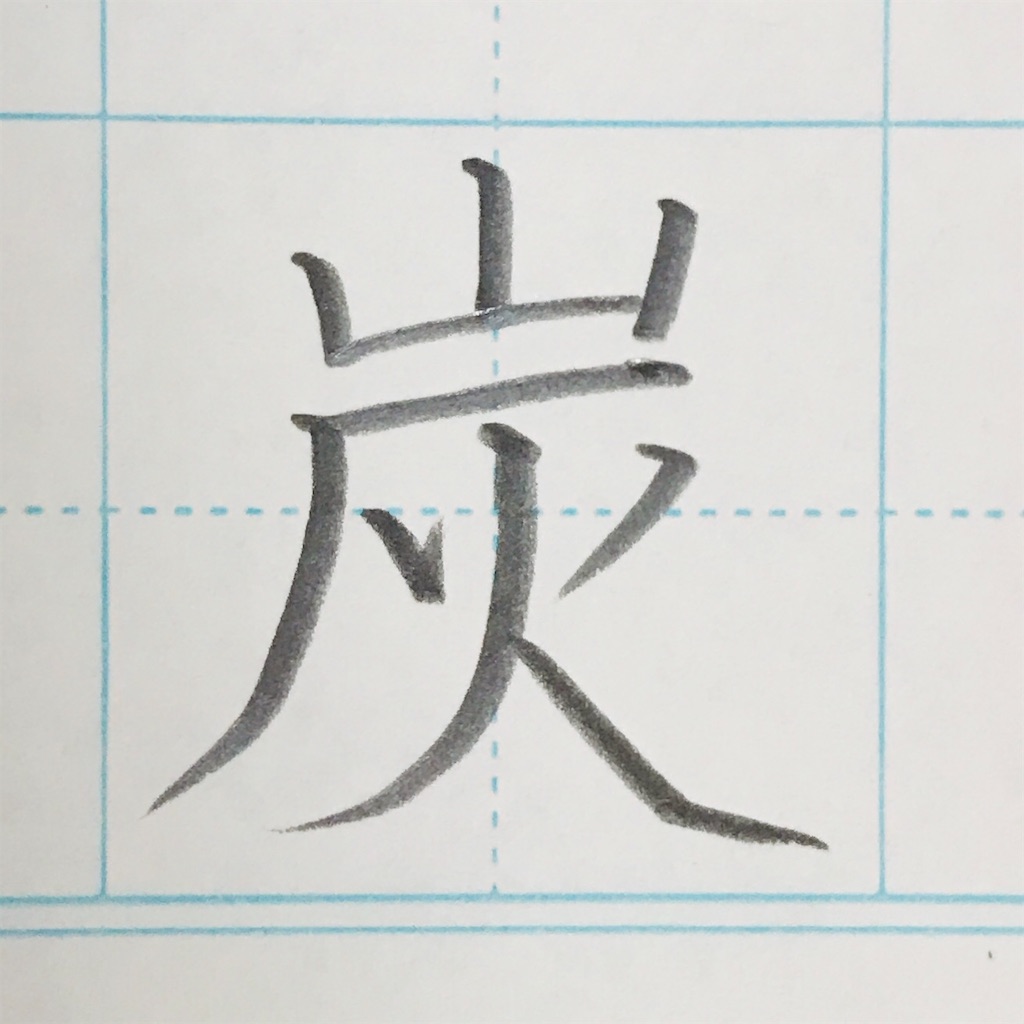
「炭」の画数
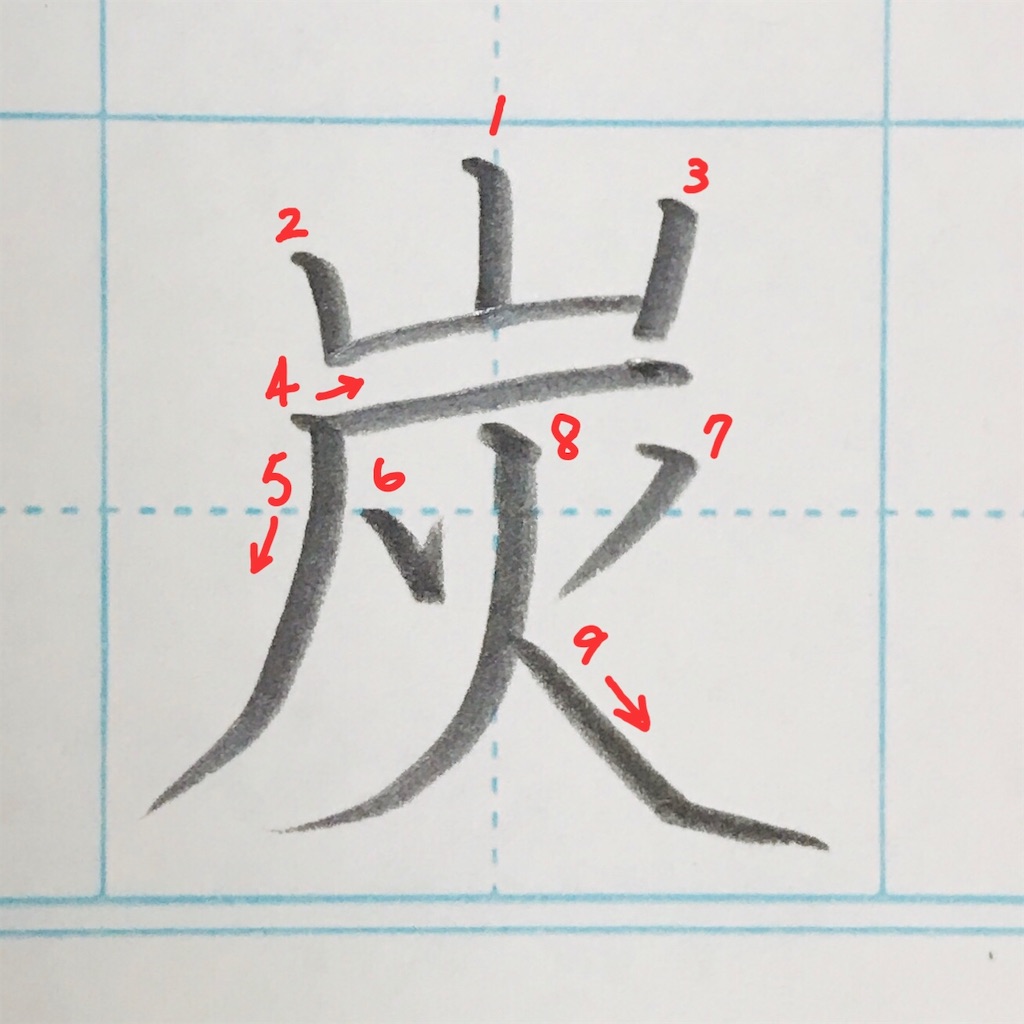
9画です。
「炭」のポイント
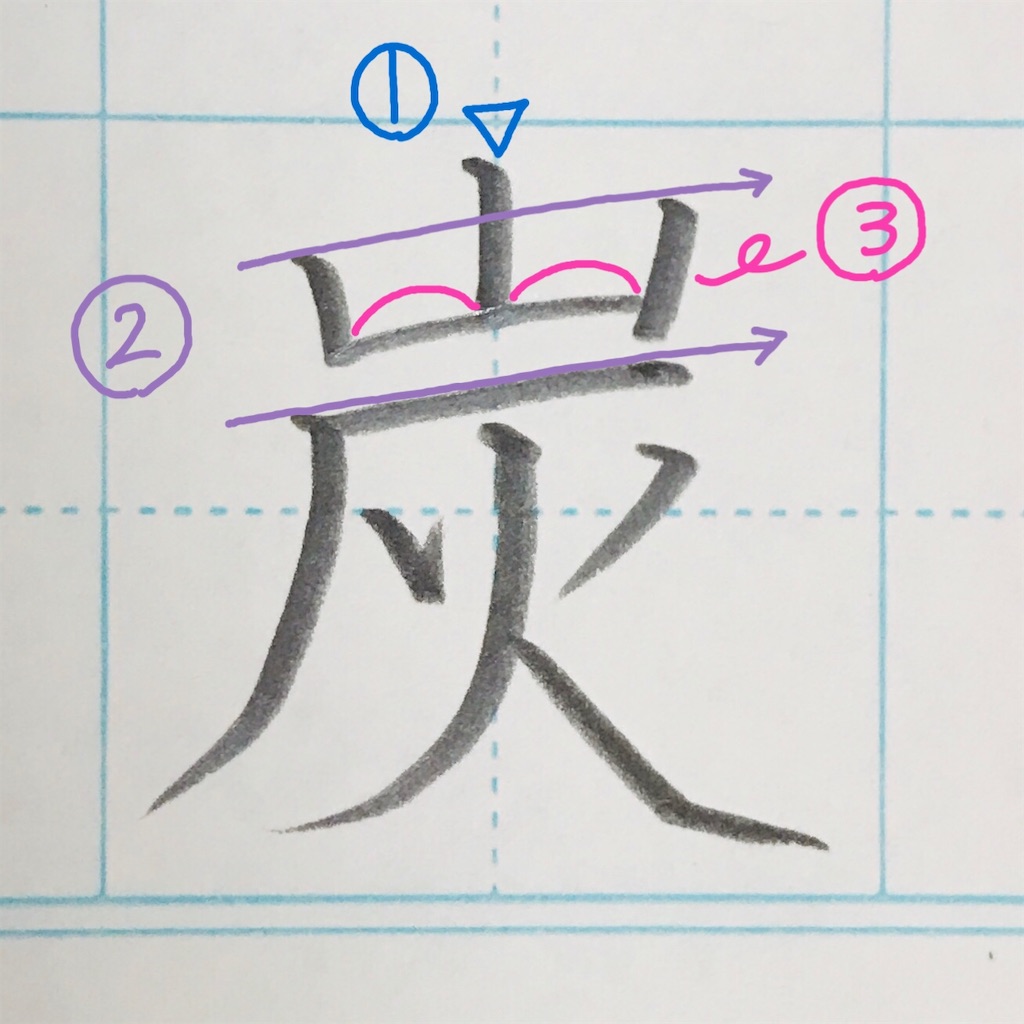
①1画目で中心が決まるので、狙いを定めて、真っ直ぐに。
②2画目3画目のはじめは、横画の右上がりに合わせるときれいです。
③間隔を等しくしましょう。
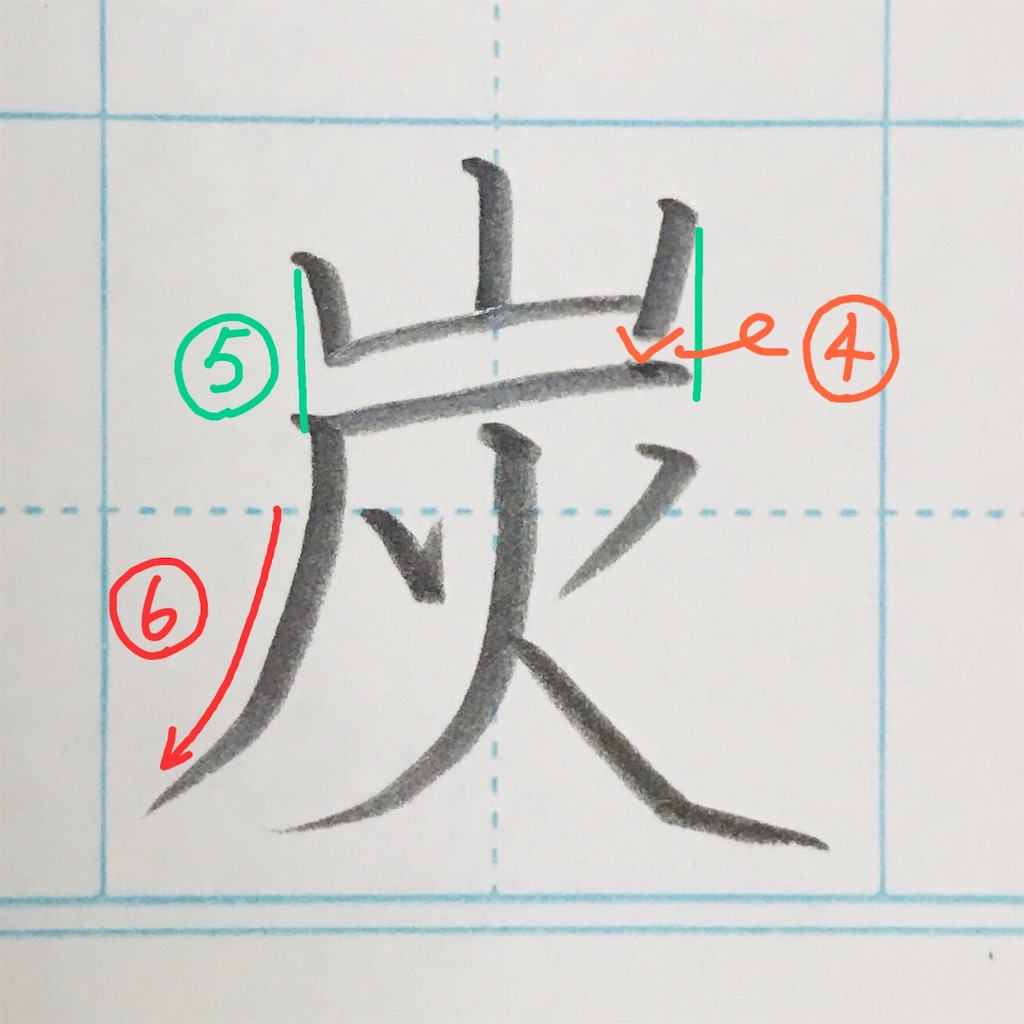
④縦画を出します。(出しすぎると、下の横画の邪魔になるので注意!)
⑤山の横幅と、「灰」の上部をだいたい揃えます。
⑥5画目は短くせず、下の方までしっかりと伸ばして払います。
⑦「火」の中心は、文字の中心よりほんの少し右です。
(4画目の横画の中心を狙うと良いです。)
⑧6画目7画目も右上がりの関係にします。
⑨「火」の下は揃えます。
(左払い、最後をしっかり曲げると◎)
完成!